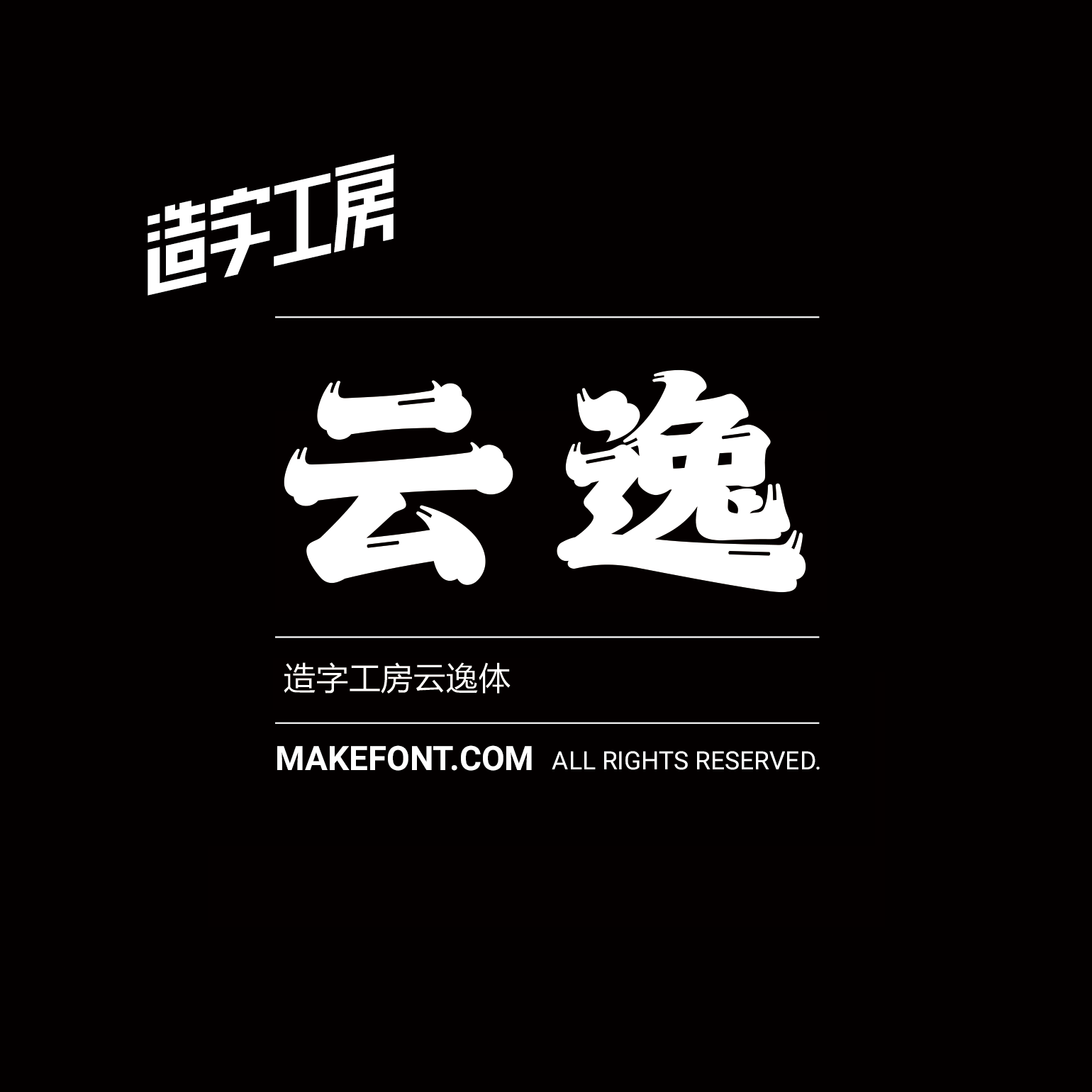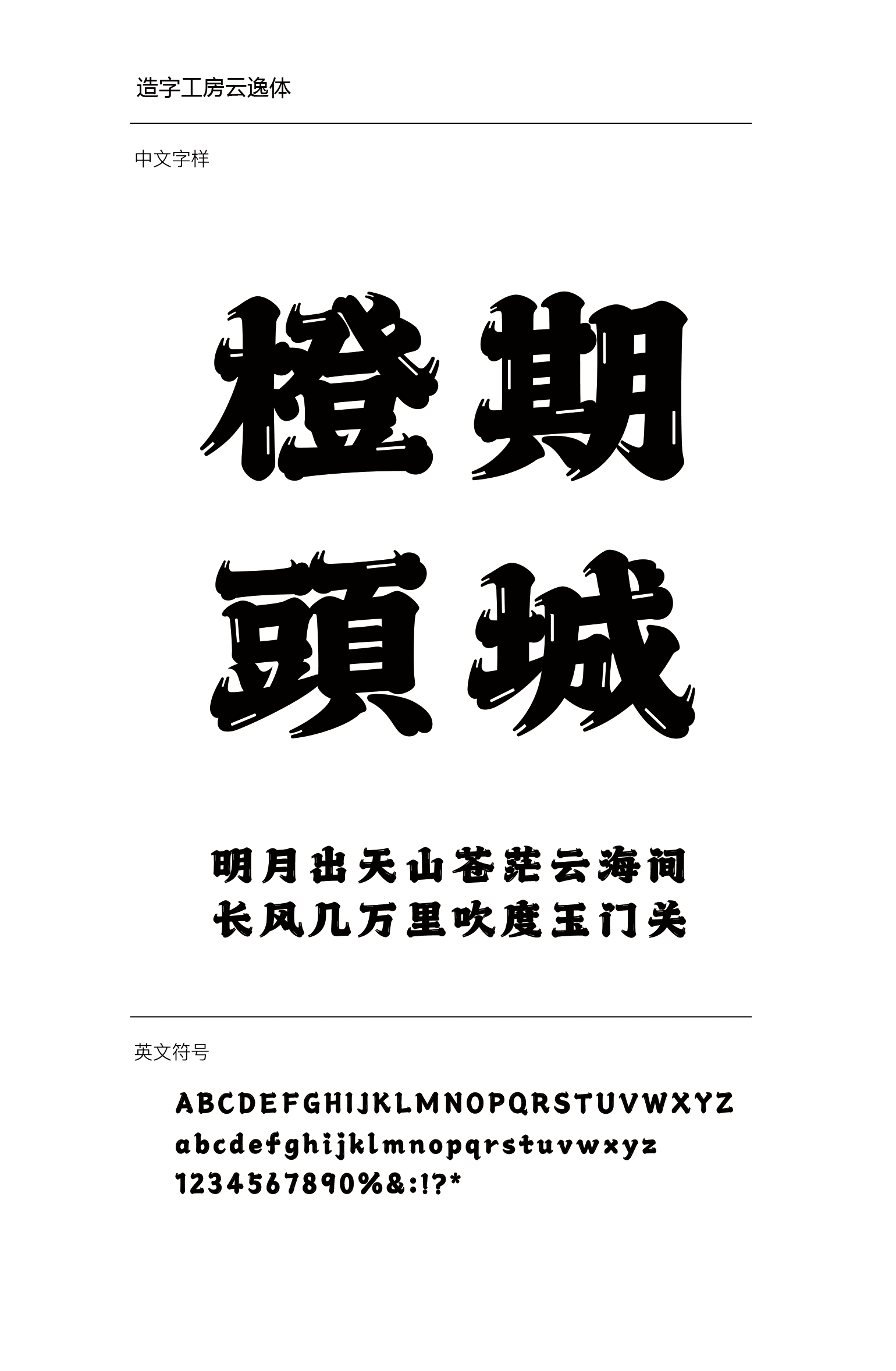
造字工房云逸体设计说明
造字工房云逸体是一款结合髭文字进行设计的标题字体。字体以疏朗开阔的骨架结构为基底,加之髭文字浑厚遒劲的笔画特征,整体呈现奇宕洒脱的美学特质。本字体为简体字库,采用OpenType/CID格式,Adobe-GB1-5编码。基于中华人民共和国GB2312-80字符集标准,另按需添加101个汉字。共收容字数6864CJK汉字,ASCII常用字符100个。